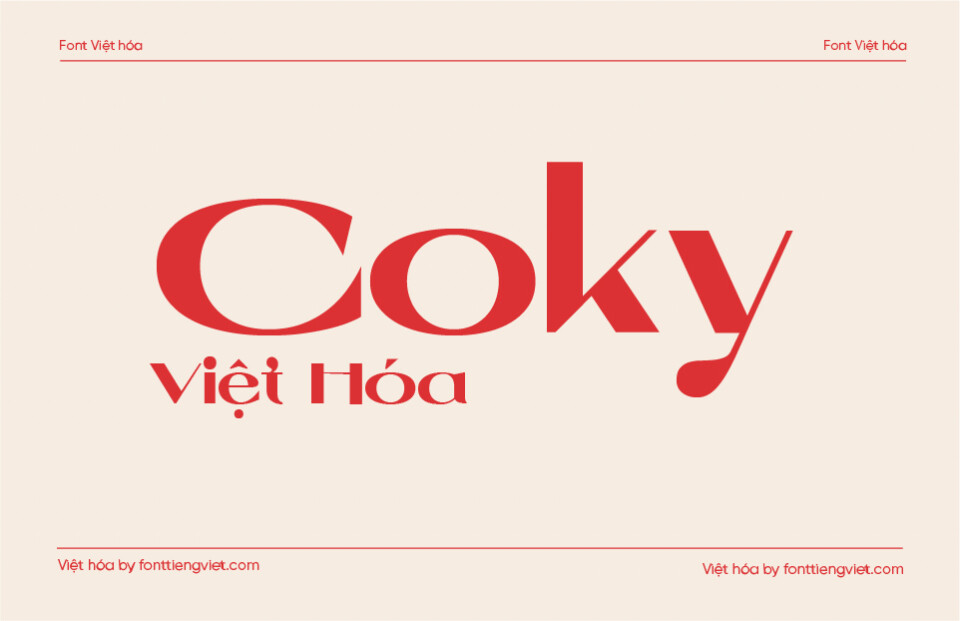
Tải Font Việt hóa 1FTV VIP Coky Miễn Phí Cho Thiết Kế Sáng TạoGiới thiệu về Font Việt hóa 1FTV VIP CokyTrong thế giới đồ họa hiện đại, việc tìm kiếm một bộ Font Miễn Phí chất lượng và phù hợp với ngôn ngữ tiếng Việt luôn là ưu tiên hàng đầu của các nhà thiết kế. Font Việt hóa 1FTV VIP Coky nổi lên như một lựa chọn hoàn hảo nhờ phong cách thiết kế độc đáo, mang đậm nét trẻ trung và hiện đại. Đây là bộ phông chữ được tinh chỉnh kỹ lưỡng về dấu câu, giúp người dùng tại Việt Nam dễ dàng ứng dụng vào các dự án từ học tập đến công việc chuyên môn mà không lo lỗi hiển thị. Với đường nét mềm mại nhưng vẫn giữ được sự chỉn chu, bộ font này thực sự là một làn gió mới cho cộng đồng sáng tạo nội dung số.Đặc điểm nổi bật của Font Việt hóa 1FTV VIP CokyThiết kế hiện đại và linh hoạtFont Việt hóa 1FTV VIP Coky sở hữu cấu trúc chữ cái rất đặc biệt với các nét bo tròn tinh tế, tạo cảm giác thân thiện và dễ gần. Điều này khiến bộ font trở nên cực kỳ phù hợp cho các bạn học sinh, sinh viên khi làm bài thuyết trình hoặc thiết kế thiệp mời, poster sự kiện trường học. Khả năng hiển thị tốt trên cả màn hình điện từ lẫn bản in là một điểm cộng lớn, giúp thông điệp của bạn luôn rõ ràng và ấn tượng. Sự cân bằng giữa các khoảng cách chữ (kerning) đã được tối ưu hóa, mang lại trải nghiệm đọc mượt mà và không gây mỏi mắt cho người xem.Tính ứng dụng đa dạng trong nhiều lĩnh vựcKhông chỉ giới hạn trong môi trường giáo dục, bộ phông chữ này còn được các blogger và người sáng tạo nội dung trên mạng xã hội ưa chuộng. Bạn có thể sử dụng Font Việt hóa 1FTV VIP Coky để làm tiêu đề video, ảnh bìa Facebook hoặc thiết kế giao diện ứng dụng di động. Với tính năng hỗ trợ đầy đủ bảng mã tiếng Việt, người dùng không còn phải đối mặt với tình trạng các ký tự có dấu bị nhảy font hay sai định dạng. Đây là yếu tố then chốt giúp quy trình làm việc trở nên chuyên nghiệp và tiết kiệm thời gian đáng kể cho các designer bận rộn.Hướng dẫn sử dụng và cài đặt hiệu quảCài đặt trên máy tính và ứng dụng đồ họaĐể bắt đầu sử dụng Font Việt hóa 1FTV VIP Coky, bạn chỉ cần tải tệp định dạng .otf hoặc .ttf về máy tính. Sau đó, nhấn chuột phải vào tệp và chọn Install để hệ thống tự động tích hợp vào thư viện phông chữ dùng chung. Bộ font này tương thích tốt với các phần mềm phổ biến như Microsoft Word, PowerPoint và bộ công cụ Adobe như Photoshop, Illustrator. Việc kết hợp font này với các tông màu pastel hoặc màu sắc rực rỡ sẽ giúp bản thiết kế của bạn thêm phần sinh động và thu hút sự chú ý của người xem ngay từ cái nhìn đầu tiên.Lưu ý khi phối hợp phông chữKhi sử dụng Font Việt hóa 1FTV VIP Coky, bạn nên kết hợp nó với một font chữ không chân (sans-serif) đơn giản cho phần nội dung chi tiết. Sự tương phản này giúp nhấn mạnh các tiêu đề chính mà vẫn giữ được sự hài hòa tổng thể cho trang văn bản. Hãy chú ý đến kích thước chữ để đảm bảo tính thẩm mỹ, tránh việc nhồi nhét quá nhiều phông chữ khác nhau trong cùng một tác phẩm thiết kế.Kết luận về bộ Font Việt hóa 1FTV VIP CokyHy vọng rằng bộ phông chữ này sẽ trở thành công cụ đắc lực trong hành trình sáng tạo của bạn. Với sự kết hợp giữa thẩm mỹ hiện đại và tính tiện dụng cao, đây chắc chắn là nguồn tài nguyên không thể thiếu. Hãy truy cập ngay vào Font Miễn Phí, Font Việt Hóa, Font Việt hóa 1FTV VIP Coky để làm mới bộ sưu tập cá nhân của mình. Chúc các bạn có những tác phẩm thiết kế tuyệt vời và đầy cảm hứng với sự trợ giúp từ bộ font đặc biệt này trong thời gian tới.
Font Việt hóa 1FTV VIP Coky